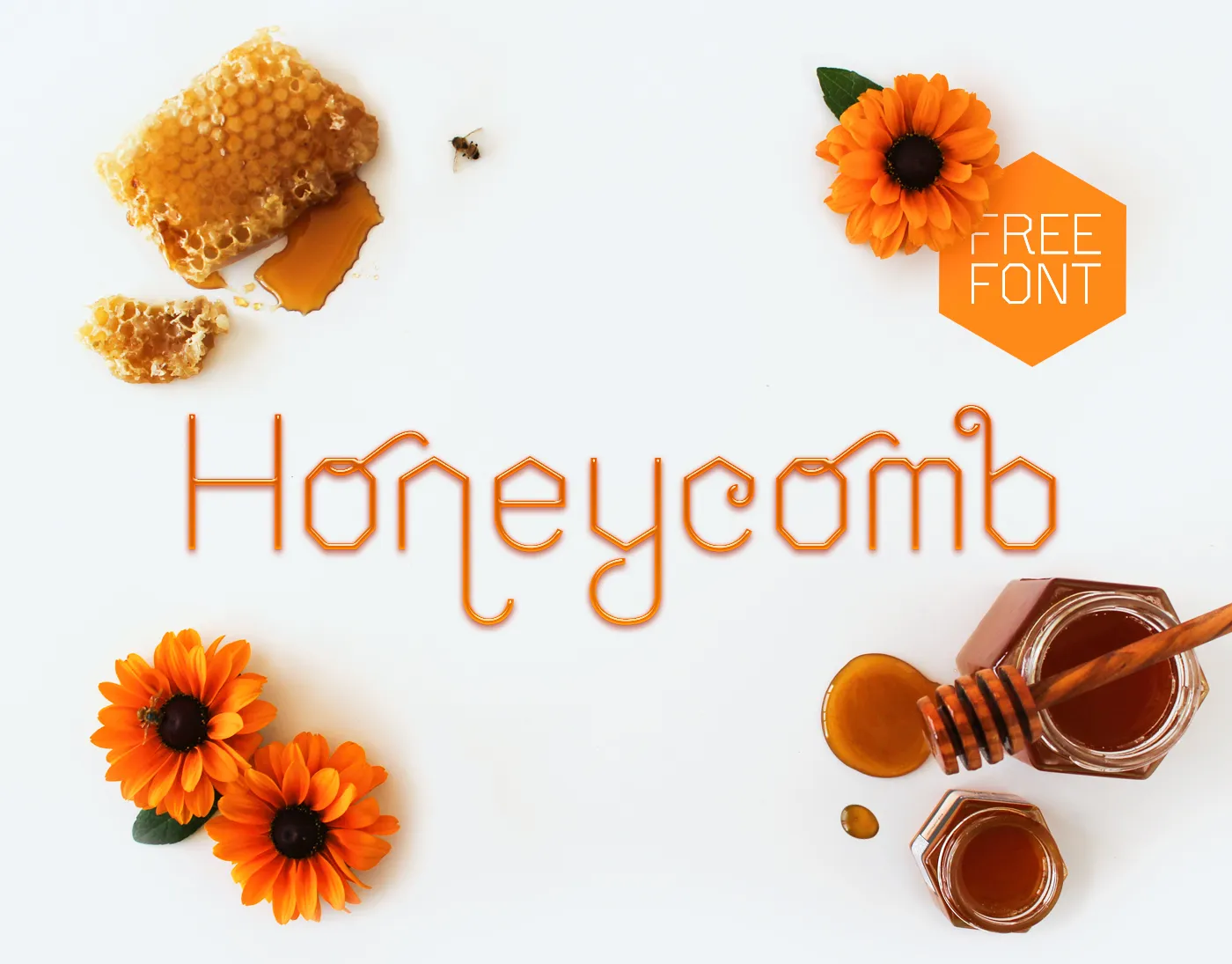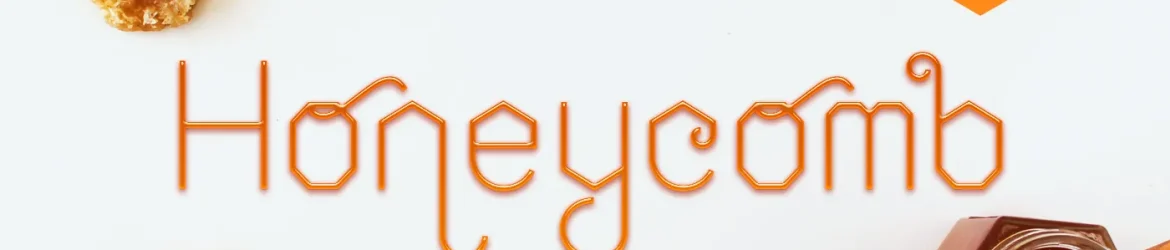
Introduzimos a você a Honeycomb Font Family, uma nova família de fontes que traz um toque descontraído ao seu projeto. Especialmente criada pelo designer Hamilton, esta fonte abraça os elementos sem serif que tornam as fuentes sans-serif tão populares atualmente. Com a Honeycomb Font, você ganha uma variedade de opções – incluindo negrito e itálico personalizados para uma experiência impecável. A Honeycomb foi pensada para ser fácil de ler em qualquer formato: seja o texto principal ou mesmo os links na sua página web, ela mantém um equilíbrio elegante e moderno. Seja você um designer gráfico atento às últimas tendências ou apenas alguém querendo dar um toque especial ao seu design, a Honeycomb Font Family é perfeita para seus projetos. E como sugestão adicional, a família de fontes vem em uma incrível combinação de 6 opções diferentes, cada uma com sua própria personalidade única. Descubra o que a Honeycomb pode fazer pela sua próxima criação!